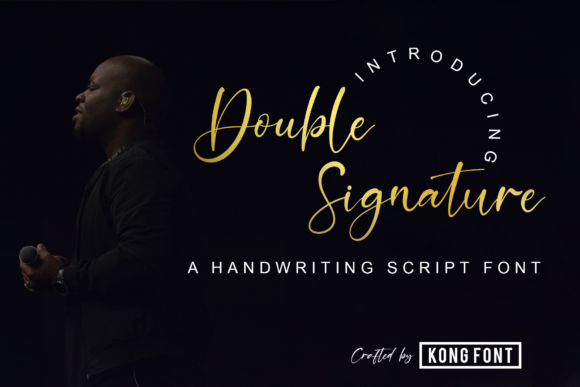
Double Signature
Double Signatureのような高品質の素材をお探しの場合、このプレミアムパッケージはクリエイティブなプロジェクトに素晴らしい選択です。
POD(オンデマンド印刷)製品、結婚式の招待状、またはソーシャルメディアのグラフィックを作成している場合でも、Double Signatureは理想的です。